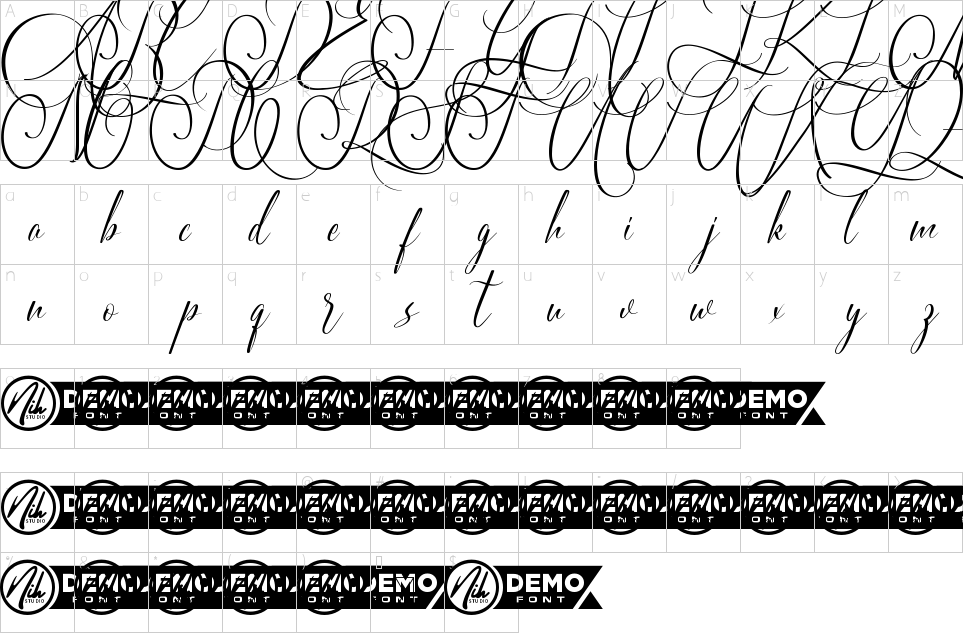
Descubra Monica Harper, uma elegante e delicada fonte grátis disponível para você. Desenvolvida por nihstudio, esta fonte vem em versões para Windows e Mac. Monica Harper é perfeita para adicionar um toque diferenciado a seus projetos gráficos, seja para sites, logomarcas ou editoriais. Com sua estilização suave e personalizável, Monica Harper é uma escolha conveniente para qualquer designer que busca uma fonte grata e elegante para suas criações digitais. Recomendamos Monica Harper para aqueles buscando um estilo elegante que não compromete a legibilidade. Download agora e dê um toque único a seus projetos.